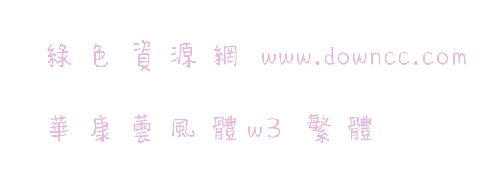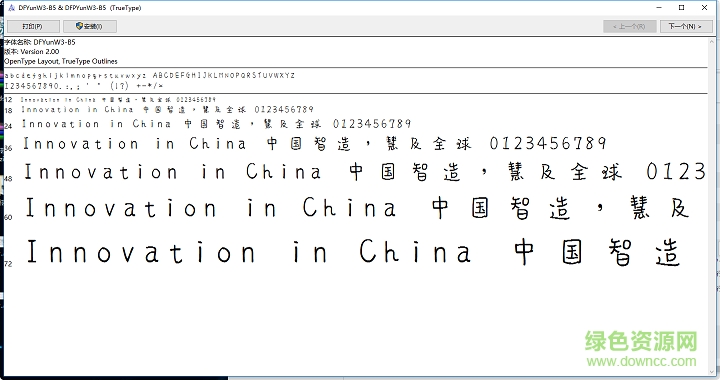
華康蕓風(fēng)體w3 繁體是一款萌系字體。圓潤(rùn)的外形獲得了設(shè)計(jì)師不少喜愛。適用于廣告,海報(bào)的設(shè)計(jì),不少設(shè)計(jì)師都喜歡。歡迎來綠色資源網(wǎng)下載。
華康字體以其清新自然的設(shè)計(jì)、繼承也創(chuàng)新的完美結(jié)合、全球觀的推廣營(yíng)銷,使得其贏得相當(dāng)比例的用戶。